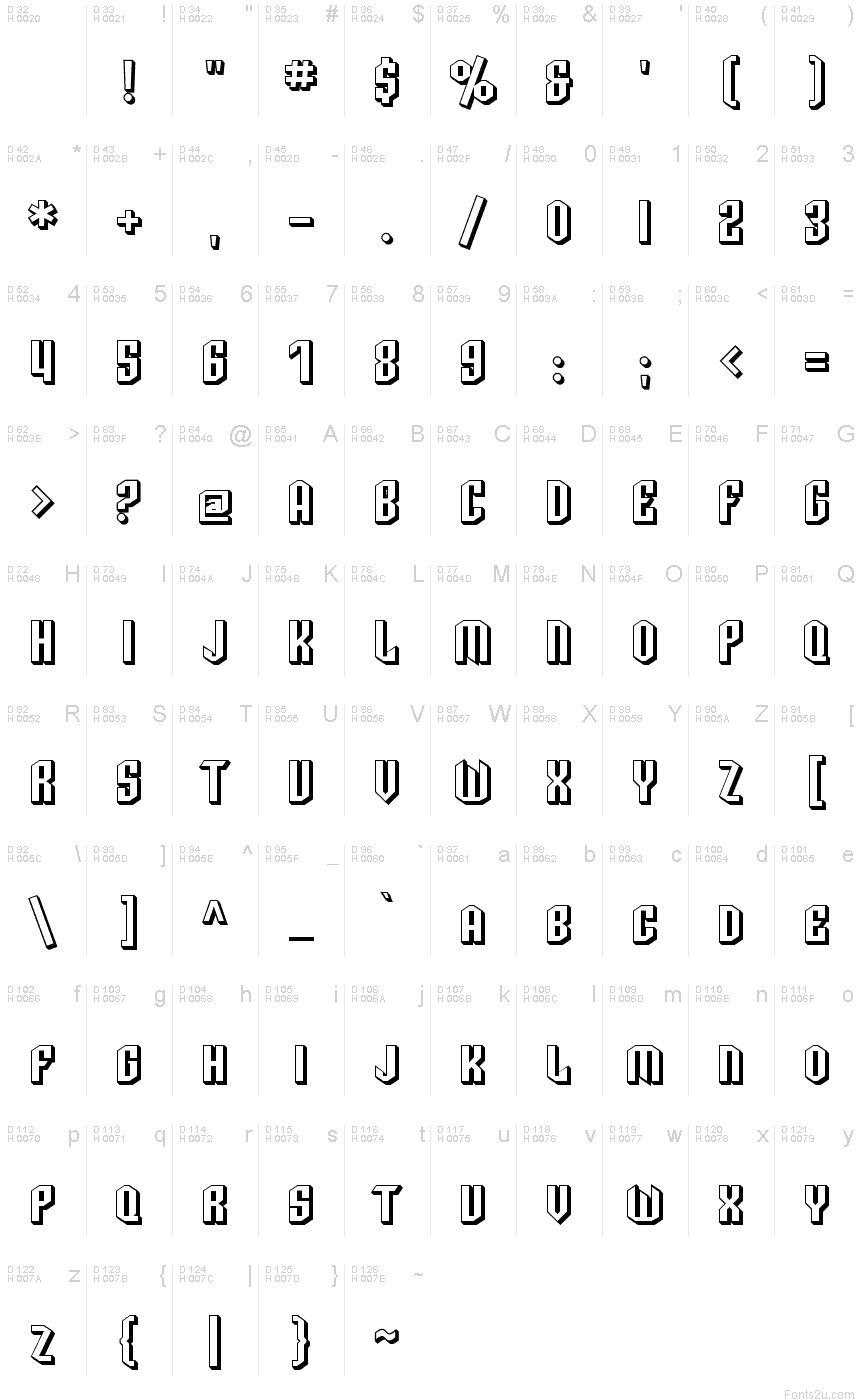
SF Archery Black SC Shaded
SF Archery Black SC Shaded di ShyFonts Type Foundry è un font display techno gratuito dal carattere spigoloso, ispirato all'era dei videogiochi arcade. Le lettere sono alte, squadrate e dagli angoli netti; l'ombra sfalsata conferisce al font un aspetto di metallo tagliato, che richiama i tabelloni segnapunti piuttosto che un design futuristico levigato.
Si adatta perfettamente a titoli di poster, grafiche sportive, menu di gioco, copertine di fumetti e monogrammi d'impatto dove le lettere devono farsi notare. Essendo un font gratuito, funziona al meglio in brevi testi display e titoli: l'ombra integrata dà a ogni parola una spinta tridimensionale decisa, senza bisogno di ulteriori effetti.